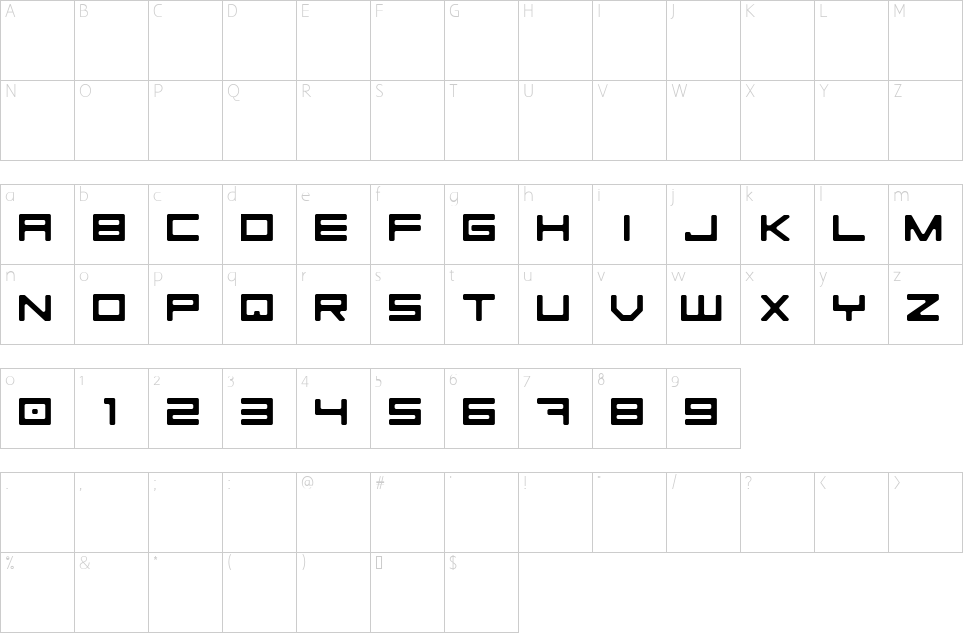
A fonte Basica – Future é um belo exemplo de uma fonte moderna e futurista, ideal para ambientes de design moderno e tecnológico. Desenvolvida pelo designer Qbotye Fonts, essa fonte vem em versões para Windows e Mac, permitindo um uso ilimitado e sem restrições. Com seu estilo clean e minimalista, a Basica – Future é perfeita para aplicativos de design gráfico, criação de logotipos, design de jogos e mais. Com apenas 8.548 downloads, é uma fonte que oferece um design único e inovador ao seu projeto. Se você está buscando uma fonte moderna para seus projetos, a Basica – Future pode ser uma ótima escolha. Descubra o seu estilo único hoje!